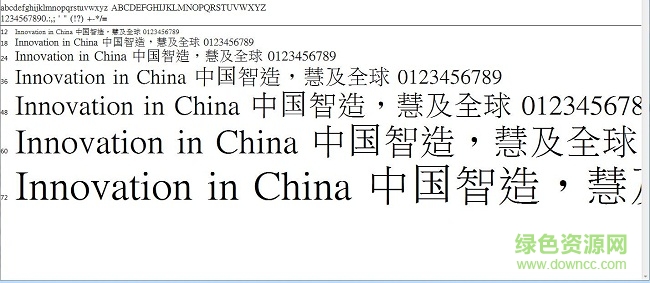
蘋果儷宋 pro字體是一款橫輕直重的宋體字體,字身秀美,大方溫和有氣質(zhì),閱讀非常便捷,常常用在PPT或書籍的用于內(nèi)文之中,需要的朋友歡迎免費下載!
橫細(xì)堅粗,“撇如刀,點如瓜子,捺如掃”筆劃嚴(yán)謹(jǐn),帶有裝飾性的點線,字形方正典雅,嚴(yán)肅大方,是美術(shù)字體之首。
筆畫粗細(xì)一致,起筆頓頓,落筆頓頓,講究頓筆,挺拔秀麗,適合手寫體的仿宋體,當(dāng)時稱為新宋,宋體又稱為老宋。是現(xiàn)代宋體的一種。